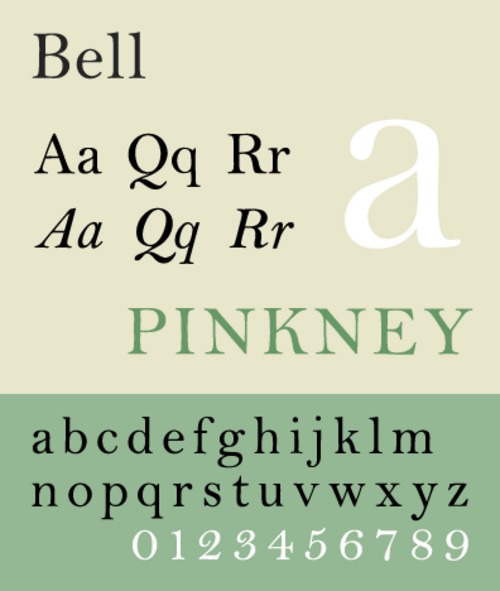
| カテゴリ | セリフ |
| 分類 | 過渡期[1] |
| デザイナー | リチャード・オースティン |
| 鋳造所 | ブリティッシュレターファウンドリー |
ベルは、 1788年に出版者のジョン・ベルが経営するイギリス文字鋳造所のためにパンチカッターのリチャード・オースティンが設計・カットしたセリフ書体に付けられた名前であり、それ以来何度も復活しています。[2] [3]
ベル書体は、多くの文字で太いストロークと細いストローク、およびボール ターミナルのスタイリッシュなコントラストを特徴とする精密な外観を備えています。この書体は、大陸で人気を博していた過激なディドネスタイルの書体、特にディドット家の作品の影響を受けています。ただし、デザインはそれほど厳格ではなく、初期のバスカービル書体や少し後のブルマー書体にいくらか似ています。[4] [5] [6]数字は、初期の可変の高さの数字とは対照的に、大文字の約 4 分の 3 の高さで固定またはライニングされているのが特徴です。[a]数字には、当時の鋼のようなカリグラフィを彷彿とさせる多くの精巧なディテールがあり、そのうちのいくつかがわずかに傾いていることから、ウォルター トレイシーは、オースティンが書体の例に従っているのではないかと示唆しました。[7]イタリック体では、バスカービルと同様に、いくつかの文字に装飾があります。[b]
短期間人気があった後、この書体はイギリスでは使われなくなり、オースティンの後の書体はスタイルがかなり異なっているが、20世紀初頭頃にはアメリカで職人の印刷業者の間でコピーが人気となった。その歴史は1920年代後半から1930年代初頭にかけて歴史家スタンレー・モリソンによって研究され、モリソンの雇用主であるモノタイプ社は1931年にこの書体を復活させ、特に高品質の紙への印刷で人気を博した。モリソンはオースティンの「並外れた技術的才能」を称賛し、彼のベル書体を「精度においてこれまでのイギリスや大陸の活字印刷をすべて上回り、ボドニやバスカービルに対しても同等の独立性を維持している」と評した。[8]
モノタイプ社によるベル書体のデジタル化の他に、ポール・バーンズらが光学サイズでオースティン書体を専門的に翻案した「オースティン」という書体がコマーシャルタイプ社から販売されている。[9] 2017年現在、 デイリー・テレグラフ社などが使用している。[10] [11] [12]オースティンのオリジナルの母型はスティーブンソン・ブレイクが所有し、現在はロンドンの タイプ博物館のコレクションに収められている。
歴史
革新的な書籍および新聞出版者ジョン・ベルは、フィルマン・ディドのためにカットされた当時のフランス語の書体の洗練性とコントラストに感銘を受け、オースティンに彼のブリティッシュ・レター・ファウンドリーで販売する新しい書体の制作を依頼した。[13]オースティンはかつて彫刻文字のカッターであり、パンチカッターとしてキャリアを積んだ。ベルは、ディドのように太い線と細い線の鮮明なコントラストを持つ、くっきりとしたセリフ付きの書体を希望した。しかし、デザインはより伝統的なスタイルである。モズレーは「セリフはシャープにカットされているが、フランス語の書体の厳しい括弧なしの線ではない...新しいフランスのローマン体と、バスカーヴィルによって確立された流麗な筆記体のイタリック体の融合である」と書いている。[3]
スタンレー・モリソンは、この書体は後に、ローマン体、つまりレギュラー体とイタリック体が効果的に調和したイギリス初の書体であると評した。この書体は新聞や雑誌の印刷で人気を博した。この書体には、当時世界的に普及した2つの革新、すなわち「長いs」の全面的な廃止と、すべて同じ高さのライニング数字が特徴的だった。オースティンの伝記作家アラステア・ジョンストンは、この書体がイギリスの書体デザインにおける「輝かしいが短命な」時代を切り開いたと記している。「ロマン・デュ・ロワのボディに対してより大きな比率を持ち、バスカーヴィルのモデリングを持ちながら、より色彩豊かでセリフが細い、調和のとれた書体」である。[1] [c]ジョンストンは、ベル書体の発展は、それまでバスカーヴィルのエリート印刷でしか使われていなかった紙のホットプレスのより一般的な使用によって印刷品質が向上したことと、この時期にロンドンで高級書籍の印刷が成長したことに影響されたと示唆している。[1]歴史家のジェームズ・モズレーも、この時期には「熱圧紙の使用と、よりシンプルでより開いたページへの崇拝により、活字自体の外観が版のより目立つ特徴となり、その推進者がますます注目を集めるようになった」と書いている。 [1]本文の書体に加えて、鋳造所は装飾文字やインライン文字を販売しており、その中にはフランスの例に基づいたものもあった。 [ 1 ]
しかし、この書体の当初の成功は長くは続かなかった。それは、まずベルが英国文字鋳造所を離れ、1797年に同社を売却するに至ったビジネス上の問題と、その後1808年までに印刷の好みが劇的に変化し、極端に太い線と細い線を持つ、より暗い書体へと移行したためである。(オースティンはこの変化を不快に感じ、1819年に「ある極端からその反対への移行が行われた。したがって、18世紀にはやや不格好だった文字の代わりに、現在では極端に細い線が付いており、その繊細さを保つことは不可能である...剃刀の刃のように薄くカットされた書体が、妥当な期間その形状を維持できるとどうして期待できるだろうか[?]」と書いている。[14] ) オースティンはその後、独自の鋳造所を経営し、他の会社にパンチを販売して成功したが、後期の書体はスタイルが異なり、外観がより「モダン」になっているものもある。いくつかは、米国で人気の「スコッチモダン」スタイルに影響を与えた可能性があります。[15] 19世紀初頭以降、ベル書体はさまざまな会社のコレクションに残り、最終的にはスティーブンソンブレイクのコレクションに残りましたが、一般的には見過ごされ、ほとんど使用されませんでした。
ベルの書体は1800年以降イギリスではほとんど見られなかったが、アメリカでは人気となった。ボストンの出版者ヘンリー・ホートンが1864年にリバーサイド・プレス用の書体を購入するためにヨーロッパを訪れた際、当時の所有者であるファン・ストリート・ファウンドリーからベルを購入した。ファン・ストリート・ファウンドリーは当時、ベルを「オールド・フェイス」という名前で売りに出していた。[d]ボストンでは、この書体は銅版と呼ばれ、電鋳でコピーされた。[16] [e] 1900年にブルース・ロジャースがリバーサイド・プレスでこの書体を見つけると、彼は「ブリマー」という名前で本の制作に使用した。 ダニエル・バークレー・アップダイクはメリーマウント・プレスでこの書体の別の書体を使用し、そこでは「マウントジョイ」と呼ばれていた。[18]アップダイクと頻繁に文通していたモリソンは、この書体の品質に感銘を受け、歴史を研究した後、モノタイプ社がモノタイプのホットメタル植字システムの復刻版を開発するよう手配し、オリジナルを所持していたスティーブンソン・ブレイクと協力した。モノタイプの復刻版には、イタリック体のA、J、N、Q、T、V、 Yのスワッシュ版など、オースティンの文字のさまざまなバリエーションが含まれていた。 [f]デザイナーのヤン・チヒョルトは、多くの本のデザインでベル書体を好んで使用し、著書『タイポグラフィのデザイン』でもベル書体について言及している。
鋳造タイプ
- ベル(1788年、イギリス文字鋳造所。当時はこの名前は与えられていなかった)
- ベル(1931年、イギリスのモノタイプ)[3]
- ベル(1940年、ランストンモノタイプ、モノタイプのアメリカ支社)[18]
- ベル(1949スティーブンソン・ブレイク)[19]
デジタル版
モノタイプのデジタル版はロビン・ニコラスの監修のもと開発され、モノタイプの金属版の大型ディスプレイスタイルをベースにしている。同じ金属活字の小型版をベースにしていると思われる別のデジタル版はURW++から入手できる。[20]